書家・松岡真作氏の書き下ろしによる「墨松体」など、ダイナフォント60書体を「DynaSmart V」にて10月29日から提供開始
主に文字フォント開発、およびその関連製品の開発・販売・保守を行う、ダイナコムウェアが提供する文字フォント「ダイナフォント」のライセンス製品であるDynaSmartシリーズ「DynaSmart V」に、合計60書体の提供を2025年10月29日(水)から開始した。
著名な書家である松岡真作氏が書き下ろした書の文字をフォント化した「墨松体(ぼくしょうたい)」など、2025年秋の新書体を含めたダイナフォント合計60書体が、年間ライセンス「DynaSmart V」「DynaSmart 教育機関向けプラン」「DynaSmart 学生版」を契約ユーザーに向けに提供となる。
書家 松岡真作氏の書き下ろしによる書の文字をフォント化した新書体「墨松体」
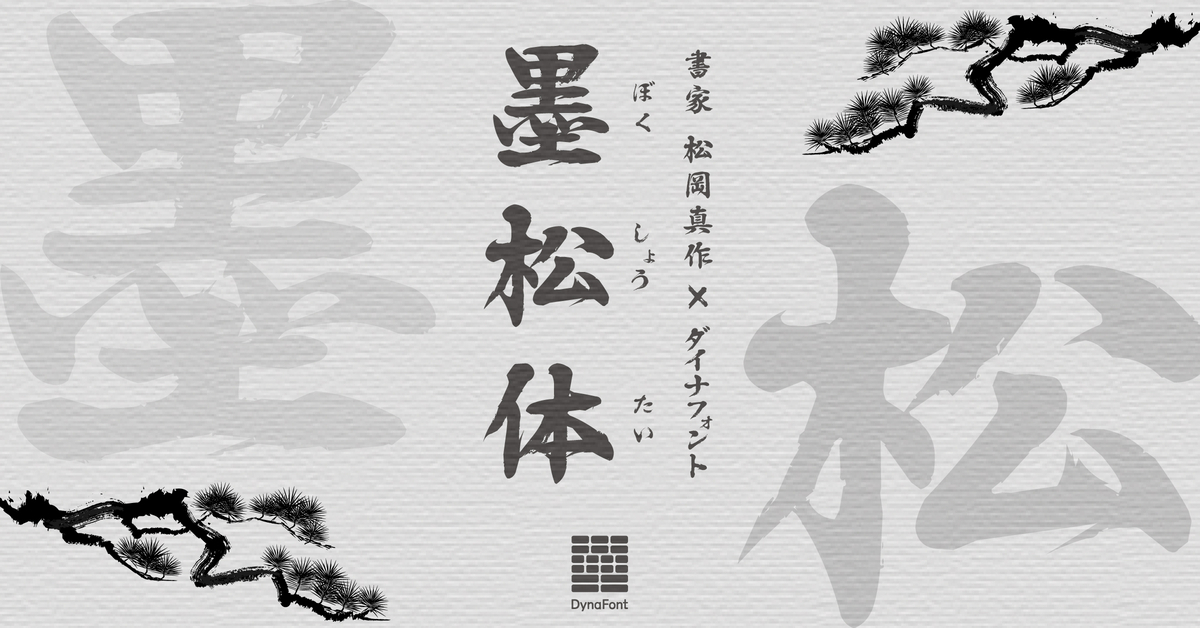
「墨松体(ぼくしょうたい)」は、テレビ番組の題字や漫画、ゲームのタイトルロゴの制作など、多岐に渡って活躍している書家である松岡真作氏が書き下ろした書の文字のフォント。力強く堂々とした佇まいと繊細な運筆による書の文字は、一目見た人を大きく惹き込む。
<松岡真作氏によるコメント>
▼書体の特徴について
今回は、書の基本を踏まえて制作に取り組ませていただきました。書体はオーソドックスなスタイルで汎用性が高く、重厚感と奥深さを備えています。また、細部の筆致にもこだわり、繊細さと力強さを併せ持つフォントに仕上げました。
▼おすすめの活用方法について
このフォントの方向性から、真剣さや誠実さを表現したい場面に適しているかと思います。歴史ものなどシリアスな展開によく馴染むのではないでしょうか。可読性にも優れているため、テロップなど視認性が求められる用途にも適していると思います。
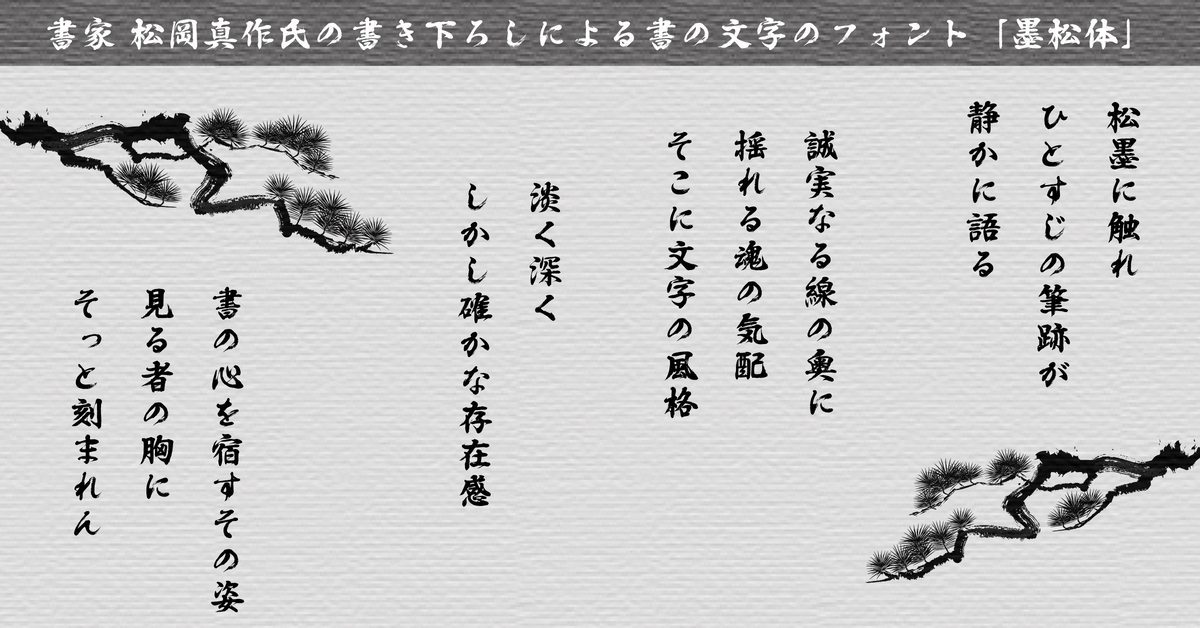
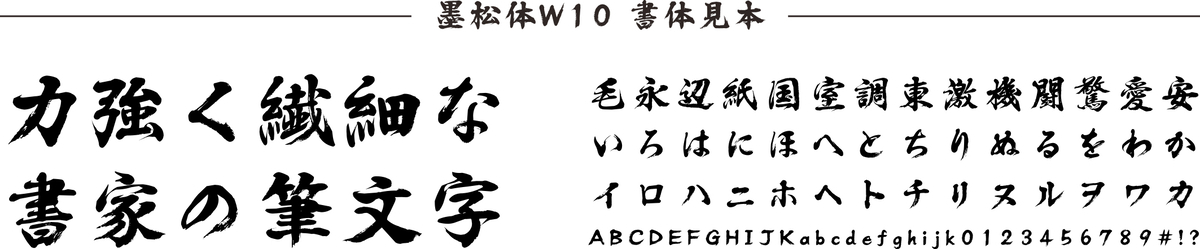
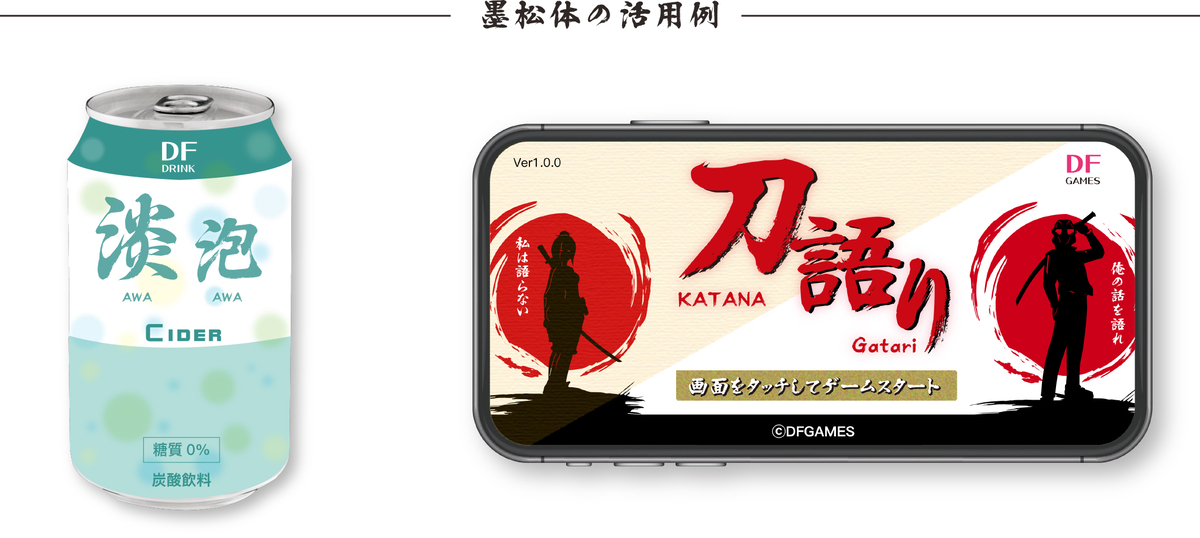
ホッとする“かな”による新しい長楕円形の文字「スティックA」
「スティック」は長楕円形の線が特徴のカジュアルなテイストのデザイン書体。やや右上がりのさらりと書いたような文字はスピード感があり、活き活きとした表情にあふれている。「スティックA」では従来の「スティック」と異なる、リラックスした線や風通しの良さを意識した、ホッとする新たな“かな”を収録した。
しさが伝わるテロップ書体「POP1体S」
「POP1体S」は既存のダイナフォントを液晶画面のあらゆるサイズでの表示に対応するようにカスタマイズしたテロップ書体シリーズの1つ。「POP1体S」のベースになっているPOP1体は広告での使用を想定したPOP系書体で、躍動感のある字形や円形のストロークが遊び心にあふれており、楽しい雰囲気を表現するのに適している。「POP1体S」はW5、W7、W9、W12の4種類の太さを使い分けることができ、映像をはじめとした画面表示で強い効果を発揮。
磨き抜かれた千磨百錬の文字“玉刻華宋”の韓国語フォント「DFJadeFangSong KR12」
「DFJadeFangSong KR12」は明朝体と楷書体のエレメントを兼ね備えた縦長の字形に力強く鋭い画線という特徴を持つ「玉刻華宋」の韓国語フォント。日本語フォント同様にW2、W4、W6の3ウエイトにて展開している。「玉刻華宋」の韓国語のローカライズはもとより宋朝体などを使用したコンテンツの韓国語のローカライズ案件、また、韓国に関連する様々な場面で幅広く活用できる。
※Adobe-Korea 1-2 準拠による18,352文字を収録している。
強い個性とデザイン性を持つ5種類の新しい欧文フォント
2025年の新しい欧文フォントである「DFBrushImpact」、「DFGoldenScript」、「DFHappyPen」、「DFSnowBloom」、「DFLinearLight」は、それぞれダイナフォントの大きな特徴である強い個性とデザイン性を持っている。ウエイトも細いモノから太いモノまでカバーして展開するなど、使いやすさにも配慮しているので、欧文が必要となる様々な場面で、各種欧文フォントを使い分けて活用できる。
悠久の歴史の文字×新しいかなデザイン「古籍五書体B」のTrueTypeフォント版
「古籍五書体B」はグッドデザイン賞を受賞するなどこれまで高い評価を受けてきた「古籍五書体」に従来のかなとは異なる新しいかなデザインを採用することで、悠久の歴史の趣を持つ文字に新たな表情を引き出した書体。